バリアブルフォント/Variable Font
バリアブルフォント(Variable Font)とは、Adobe・Apple・Google・MicrosoftといったIT業界の巨人ともいえる会社が共同で開発したOpenTypeフォント。かいつまんでいえばフォントの太さや幅、高さ、コントラスト、角丸などを調整できるフォントのこと。
また、バリアブルフォントに関してAdobeタイプデザイナーであるジョン・ハドソン氏は「ひとつのフォントファイルでありながら複数のフォントのように利用できる」フォントと定義している。
通常のフォントはフォントのウェイト(太さ)を変更する場合はそれぞれのフォントファイルを読み込む必要があるが、「バリアブルフォント(Variable Font)」を使用すればアルゴリズムを使用して1つのフォントファイルから太さや高さを変更できるため、データ容量の縮小につながる。ウェイトバリエーションの少ないフォントに関しても、ウェイトのバリエーションを増やせるなどの利点もある。
話題の「バリアブルフォント」がIllustratorとPhotoshopで使えるようになった!
Illustrator CC 2018とPhotoshop CC 2018にバリアブルフォントが搭載され、簡単にフォントの字幅や線幅、傾斜のデザインの変更が可能になったので実際にIllustratorで使用してみた。
Illustratorには、「Acumin Variable Concept」「Bahnschrift」など2019年1月現在、9書体が搭載されている。
これらの「バリアブルフォント」は、コントロールパネルでボタンをクリックするとスライダーコントロールを使用して文字を調整できる。
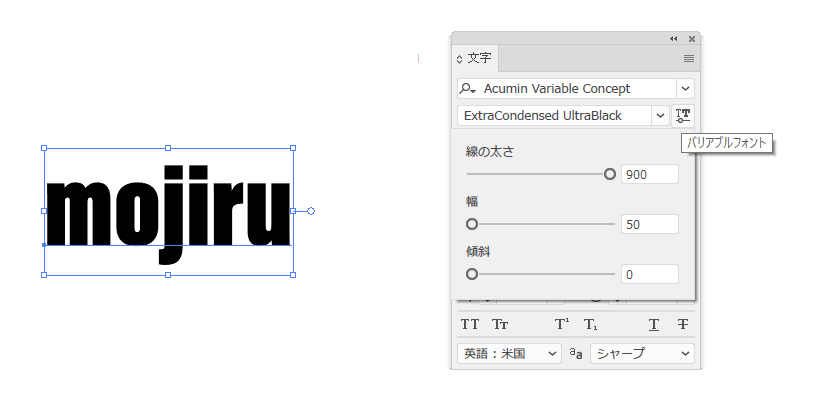
▼「バリアブルフォント(Variable Font)」線の太さを変えてみた。
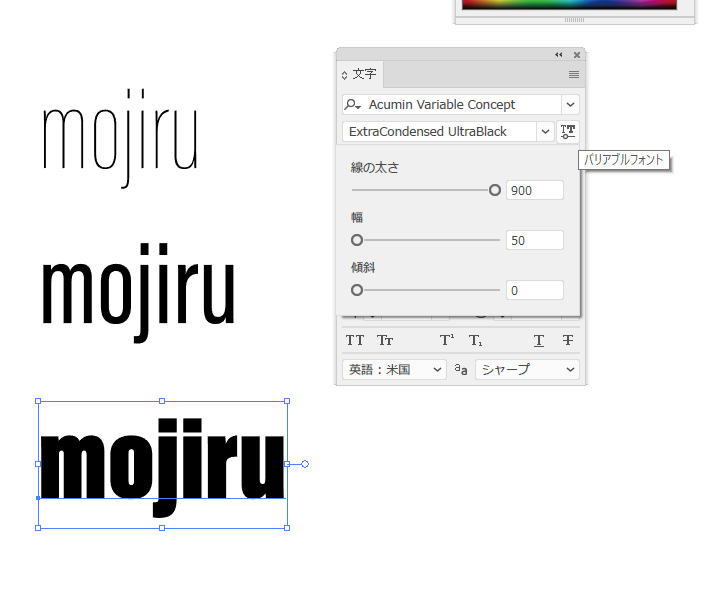
▼「バリアブルフォント(Variable Font)」幅を変えてみた。
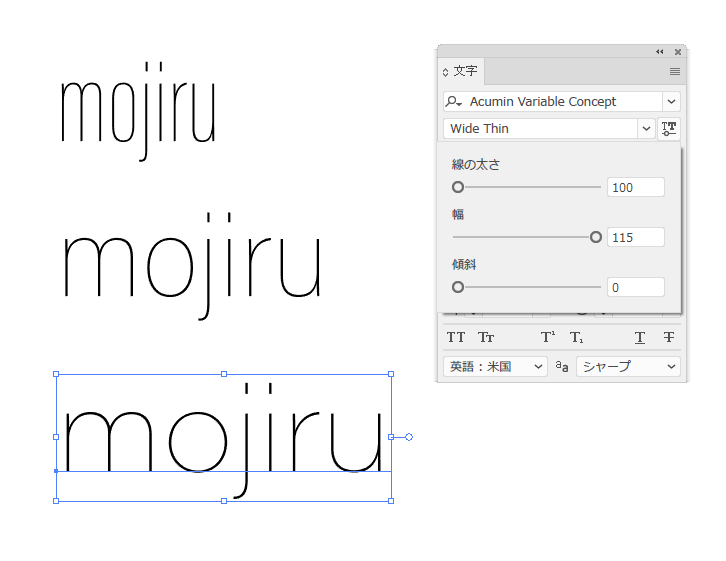
▼「バリアブルフォント(Variable Font)」傾斜を付けてみた。
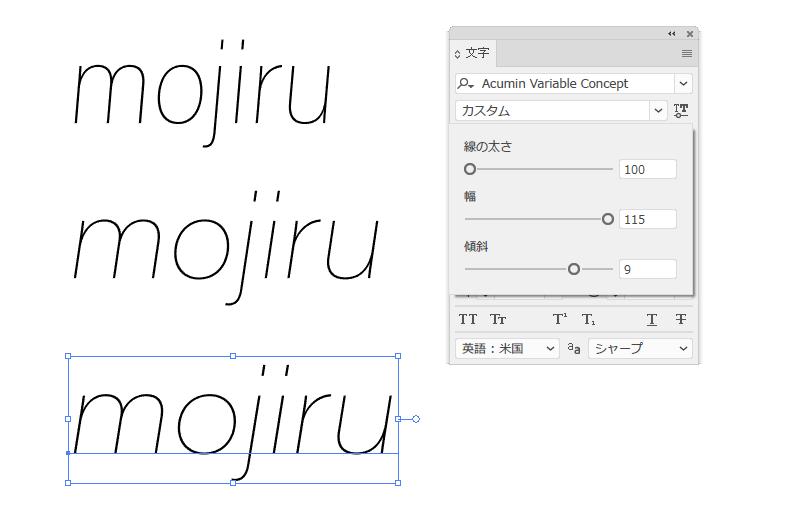
▼Photoshopでは文字パネルでバリアブルフォントを選択すると属性パネルで幅や傾斜を調整できるようになる。
Windows 10プレビュー版にVariable Font(バリアブルフォント)「Bahnschrift」が実装
米Microsoft Corporationは2017年8月23日に「Windows 10 Insider Preview」Fastリングの参加ユーザーに対してビルド16273を公開した。
このBuildにて、Windowsで初めてVariable Font(バリアブルフォント)「Bahnschrift」が実装された。
Variable Font(バリアブルフォント)「Bahnschrift」の特徴
従来のフォントは、標準とBOLD(太字)の2種類のウェイトしか使えず、それ以上に細いストロークもしくは太いストロークを使用したい場合は同じフォントファミリーの別フォントを用意する必要があったが、Microsoft、Google、Adobe、Appleらが共同で開発した新しい仕組みのフォント「Variable Font」は、1つのフォントファイルでありながらユーザーがウェイトを自由に変更できる。
Variable Fontを使ったレスポンシブレンダリングの例
「Variable Font」の特徴として、ウェイトを変更しても文字幅が変わらないためレイアウトの変更が不要になるというメリットやウェイトを変えられるためファイルサイズも小さいといった利点がある。
将来的には静的フォントが「Variable Font」に置き換わることも期待されている。
ブラウザ「Firefox 62」がVariable Font(バリアブルフォント)に対応
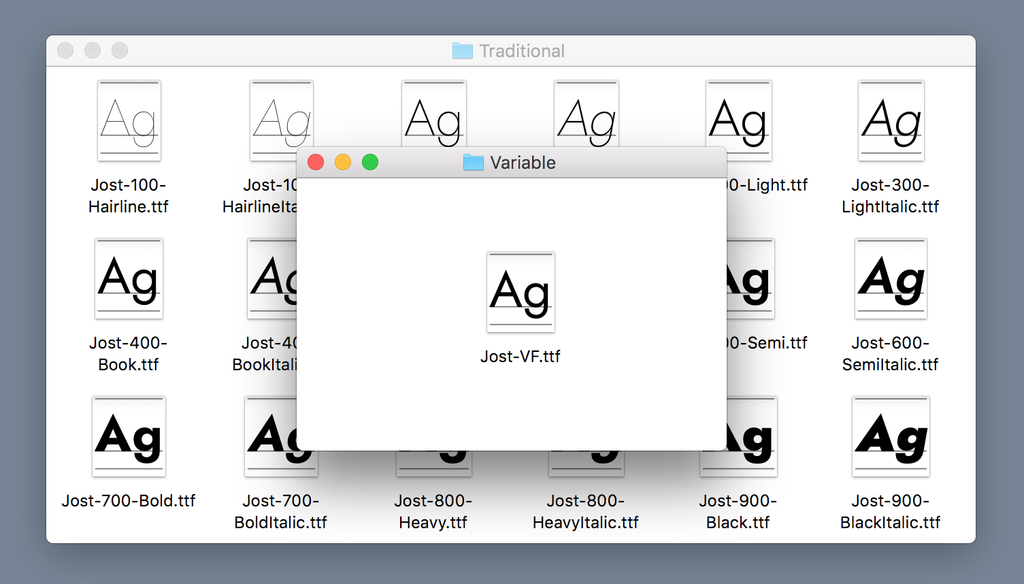
Mozillaは2018年9月4日に「Variable Fonts Arrive in Firefox 62 - Mozilla Hacks|the Web developer blog」内で、Firefox 62にVariable Font(バリアブルフォント)のデフォルトサポートを追加した事を発表した。
FirefoxがVariable Fontに対応した事で、主要ブラウザのすべてがデフォルトでVariable Font(バリアブルフォント)をサポートしたことになる。
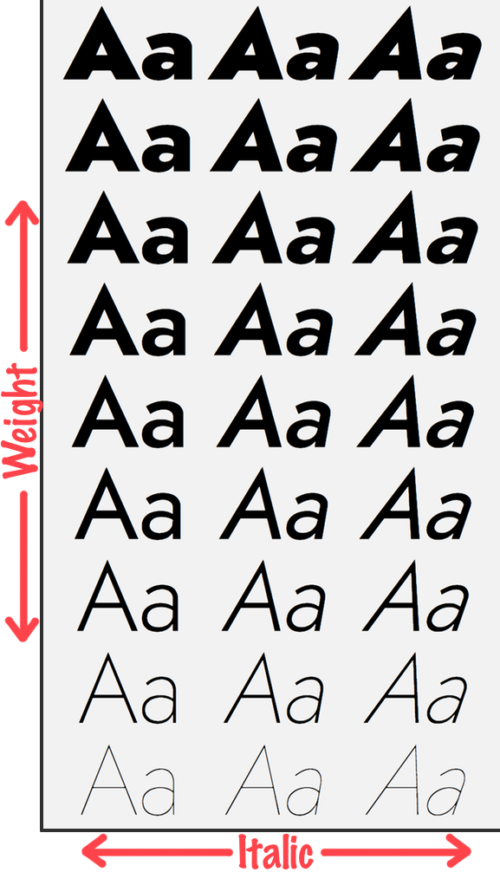
モリサワ「タイプデザインコンペティション2019」の明石賞でVariable Font(バリアブルフォントを募集
モリサワによる世界中からオリジナルタイプフェイスを募集するモリサワ主催の書体デザインアワード「タイプデザインコンペティション 2019(Morisawa Type Design Competition 2019)」の開催が2018年7月3日に発表された。
その中の賞の1つである明石賞ではOpenTypeの規格で示された「バリアブルフォント(Variable Font)」がテーマに据えられた。入賞者には、表彰状とトロフィー、副賞として次のとおり賞金を授与される。